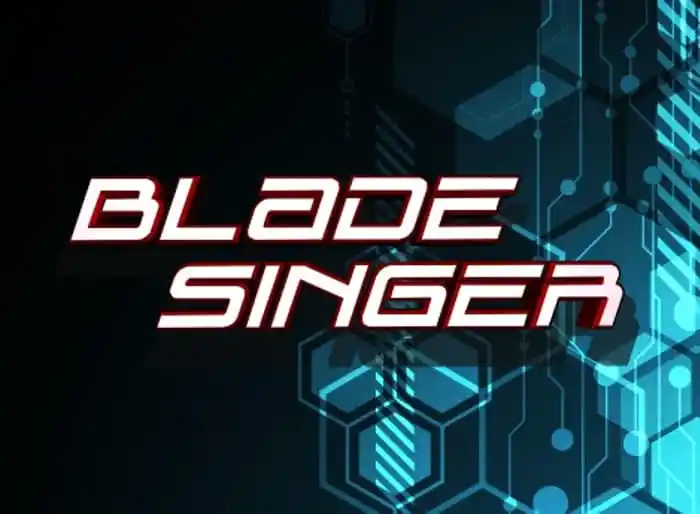
A Blade Singer Display Font é uma escolha perfeita para quem busca uma fonte que não apenas destaca, mas também se conecta com a essência brasileira. Com 25 versões disponíveis, incluindo Itálico, Semi-Itálico e suas variações condensadas e estendidas, esta família de fontes oferece um leque extenso para personalizar textos em qualquer aplicação de design digital. Ideal tanto para gráficos criativos quanto para materiais publicitários, a Blade Singer Display tem o poder de transformar mensagens digitais em obras de arte ao permitir uma variedade impressionante de efeitos. Entre as opções disponíveis, encontrarão designs 3D que destacam qualquer layout e o famoso gradient que oferece movimento à sua obra. A própria Halftone é um recurso indispensável para criar sensações vibrantes e a Laser proporciona um apelo visual moderno. Seja para projetos de marketing digital ou criações gráficas, esta família de fontes é uma escolha inteligente, que oferece tanto versatilidade quanto criatividade. A Blade Singer Display é uma opção perfeita para quem procura algo diferente e poderoso no seu portfolio de recursos digitais.